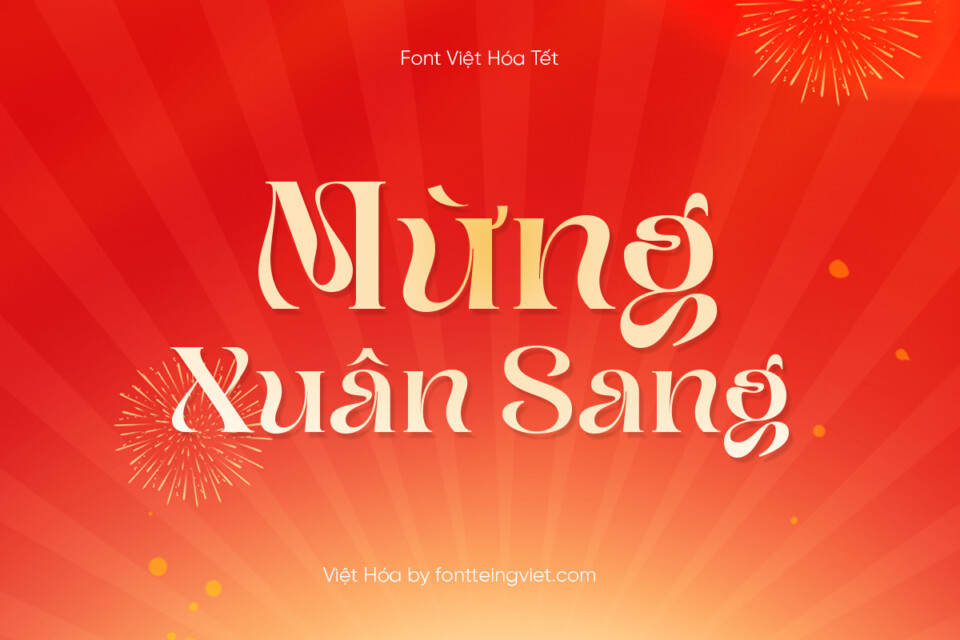
Font Việt hóa 1FTV VIP Meqanor – Font tết: Lựa chọn đẳng cấp cho thiết kế Xuân 2026Trong không khí rộn ràng của những ngày giáp Tết, việc tìm kiếm một bộ Font Miễn Phí chất lượng để làm mới các thiết kế đồ họa là nhu cầu ưu tiên của nhiều nhà sáng tạo. Font Việt hóa 1FTV VIP Meqanor – Font tết xuất hiện như một giải pháp hoàn hảo, mang đến sự kết hợp tinh tế giữa nét đẹp truyền thống và hơi thở hiện đại. Đây là bộ phông chữ được tinh chỉnh kỹ lưỡng, hỗ trợ đầy đủ tiếng Việt, giúp các bạn học sinh, sinh viên và thầy cô giáo dễ dàng tạo ra những ấn phẩm truyền thông bắt mắt cho dịp lễ hội lớn nhất trong năm.Khám phá sức hút của Font Việt hóa 1FTV VIP Meqanor – Font tếtPhong cách thiết kế độc đáo và sang trọngFont Việt hóa 1FTV VIP Meqanor – Font tết sở hữu những đường nét thanh thoát nhưng không kém phần mạnh mẽ. Với cấu trúc các chữ cái được tạo hình mềm mại, bộ font này gợi liên tưởng đến những nét bút lông uyển chuyển trên câu đối đỏ. Tuy nhiên, Meqanor không đi theo lối mòn của các phông chữ thư pháp cổ điển mà được cách tân để phù hợp với xu hướng thiết kế phẳng hiện nay. Điều này giúp bộ chữ trở nên đa dụng, từ các thiết kế in ấn truyền thống đến các banner kỹ thuật số trên mạng xã hội.Đặc điểm kỹ thuật và khả năng hiển thịMột trong những điểm cộng lớn nhất của Font Việt hóa 1FTV VIP Meqanor – Font tết chính là bộ mã ký tự được tối ưu hoàn toàn cho bảng mã Unicode. Người dùng sẽ không gặp phải các lỗi nhảy chữ hay mất dấu thường thấy ở các bộ font ngoại lai. Các nét dấu câu được đặt vị trí hợp lý, đảm bảo tính thẩm mỹ cao và sự cân đối tuyệt đối cho đoạn văn bản. Đặc biệt, độ tương phản giữa các nét thanh và nét đậm giúp thông tin truyền tải rõ ràng ngay cả khi sử dụng ở kích thước nhỏ.Ứng dụng thực tế của Font Việt hóa 1FTV VIP Meqanor – Font tết trong giáo dụcTrang trí bảng tin và thiệp chúc mừngTrong môi trường học đường, Font Việt hóa 1FTV VIP Meqanor – Font tết cực kỳ phù hợp để thiết kế tiêu đề cho các bảng tin chúc mừng năm mới. Thầy cô có thể sử dụng font này để tạo ra những tấm thiệp tri ân, phong bao lì xì mang đậm dấu ấn cá nhân của lớp học. Vẻ ngoài chuyên nghiệp của font chữ sẽ nâng tầm giá trị cho các món quà tinh thần, giúp lan tỏa niềm vui và sự ấm áp đến với mọi người xung quanh trong dịp Tết Nguyên đán.Làm slide thuyết trình và video sự kiệnBên cạnh in ấn, bộ font này còn tỏa sáng trong các bài thuyết trình chủ đề văn hóa Việt Nam. Với khả năng tương thích tốt trên các phần mềm như PowerPoint hay Canva, Font Việt hóa 1FTV VIP Meqanor – Font tết giúp các bạn học sinh trình bày ý tưởng một cách ấn tượng hơn. Những đoạn video tổng kết năm học hay clip ngắn về phong tục Tết sẽ trở nên sinh động và đậm chất nghệ thuật khi được chèn các dòng phụ đề hoặc tiêu đề bằng bộ chữ VIP này.Cách sử dụng và lưu ý khi cài đặt font chữĐể tận dụng tối đa vẻ đẹp của Font Việt hóa 1FTV VIP Meqanor – Font tết, người dùng nên kết hợp nó với các tông màu chủ đạo của mùa xuân như đỏ, vàng, và xanh lá. Việc cài đặt vô cùng đơn giản, bạn chỉ cần tải tệp định dạng .ttf hoặc .otf về máy tính, sau đó nhấn chuột phải và chọn Install. Lưu ý rằng khi thiết kế, không nên sử dụng quá nhiều hiệu ứng đổ bóng phức tạp để tránh làm mất đi sự thanh thoát tự nhiên của các đường nét chữ vốn đã rất tinh xảo.Kết luận về bộ phông chữ Meqanor Việt hóaViệc sở hữu Font Việt hóa 1FTV VIP Meqanor – Font tết trong bộ sưu tập đồ họa sẽ giúp bạn tự tin hơn khi thực hiện các dự án sáng tạo vào dịp cuối năm. Đây không chỉ là một công cụ trình bày mà còn là phương tiện truyền tải nét đẹp văn hóa Việt qua từng con chữ. Hy vọng rằng với tài nguyên Font Miễn Phí, Font Việt Hóa, Font Việt hóa 1FTV VIP Meqanor – Font tết này, các bạn sẽ tạo nên những sản phẩm tuyệt vời nhất. Chúc các bạn có một mùa Tết sáng tạo và tràn đầy cảm hứng nghệ thuật cùng bộ font chữ đẳng cấp này!
Font Việt hóa 1FTV VIP Meqanor – Font tết